一款好看的手写体会给人一种赏心悦目的感受, 今天小字给各位带来的是字体视界中5款较为好看的手写体。
印品赤壁赋体
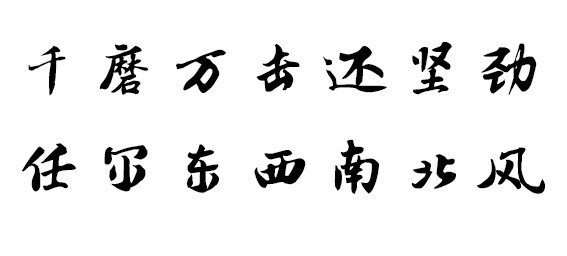
该字体源于北宋文学家苏轼创作的一篇赋,全赋在布局与结构安排中映现了其独特的艺术构思,情韵深致、理意透辟,有很高的文学地位。见字如晤,愿后人都能记住这位伟大的文学家。
三极萌娃简体
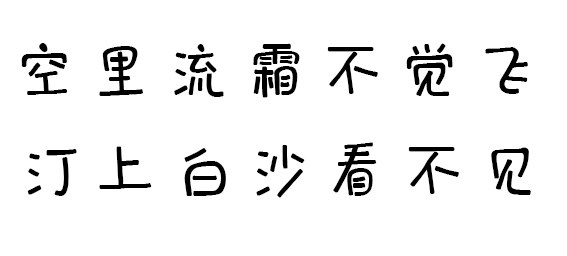
三极萌娃简体以儿童写字的特点,勾勒笔画,具有童稚之情。笔画圆润,字形轮廓统一,灵动可爱,溢于画笔,清新萌动。适用少儿类读物、书刊以及社交网络个性化用字。
汉标瘦金简体
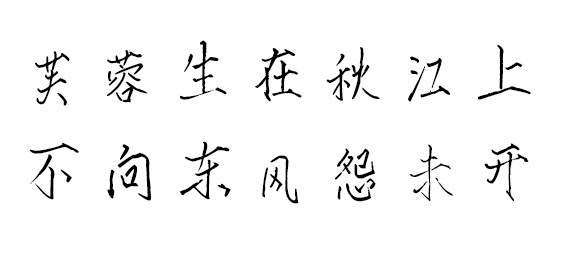
瘦金书本来偏“瘦”在实际版面中易虚化而不易远观,这款字体加粗了笔画,笔形和结构高度稳定,易读性强。其风格雍容高雅,适用于文化类的宣传设计,以及商业类品牌的广告和产品包装设计。
汉标学步体
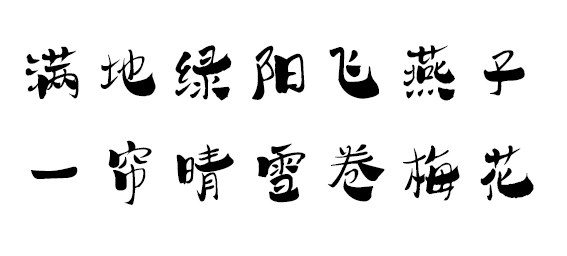
作者在创作时力求行书端庄平稳,中正安舒,字体易于识别、字型规范而不失特色。行书的运笔加入了一些抑扬顿挫及个别笔画的大舒展,形似人在抬腿迈步的感觉。
汉标智造国楷
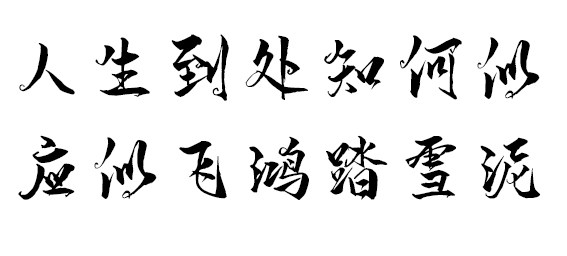
汉标智造国楷,书法气息浓厚,结字潇洒俊逸,运笔行云流水,气韵生动。适用于文艺类的书刊、品牌广告和产品包装设计,以及社交网络的个性化用字。